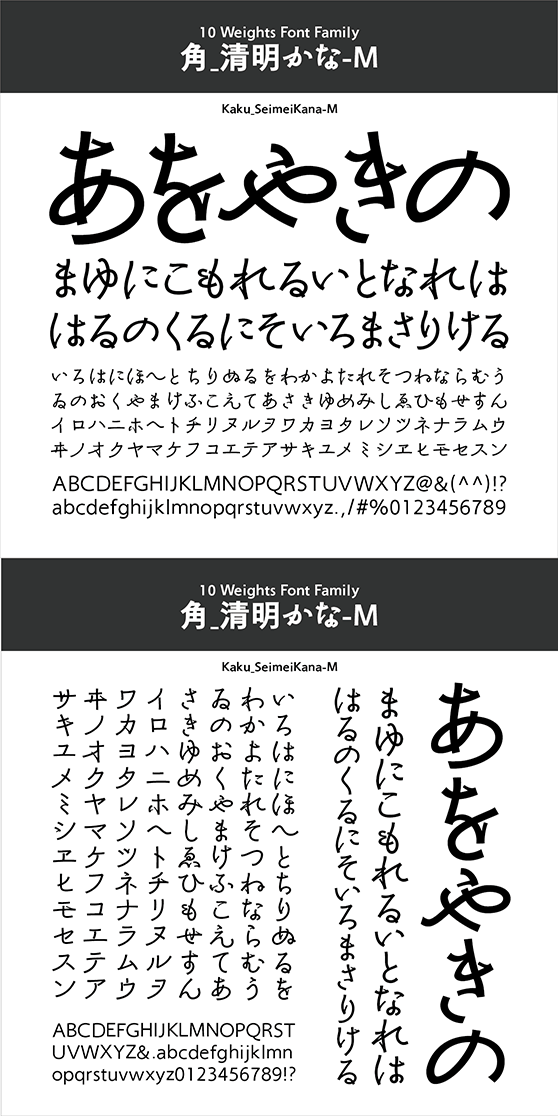
角_清明かな-M
Kaku_SeimeiKana-M
優しさと切れ味をあわせ持つかなフォント
この書体は、大好評を得ている「清明かな」のゴシック版として開発されたものです。書体名の「清明(せいめい)」は、季節の指標である「二十四節気」の5番目の節気のこと。春の息吹があふれ「すべてのものが清らかで生き生きしている」という意味です。その名の通り、伸びやかな切れ味の中に優しさ・優美さを包含した不思議な書体です。
タイプデザイナー金井和夫の普段使いの文字をベースとした、明朝・行書・楷書の複雑なフォルムイメージを持っています。また、オールドなイメージを残しつつも、その概念にとらわれず大仮名に設計してあり、近代的な組版にも対応するマルチな性格を備えています。
角_清明かなは、クリエイティブワークに「躍動感と訴求力を表現する」一助にと開発されました。和文フォントは、正方形の中に押し込めることにより、伸びやかさがなくなる傾向があります。この書体は必ずしも正方形にとらわれない自由な発想で作られています。特徴が強く、長文には不向きですが、短い本文組みや、手紙文、ちょっとした見出しに使ってみてください。躍動感に満ちた、訴求力のある紙面になるはずです。縦組み、横組みともプロポーショナル加工を加えました。また、ペアカーニングもほどこしてあります。